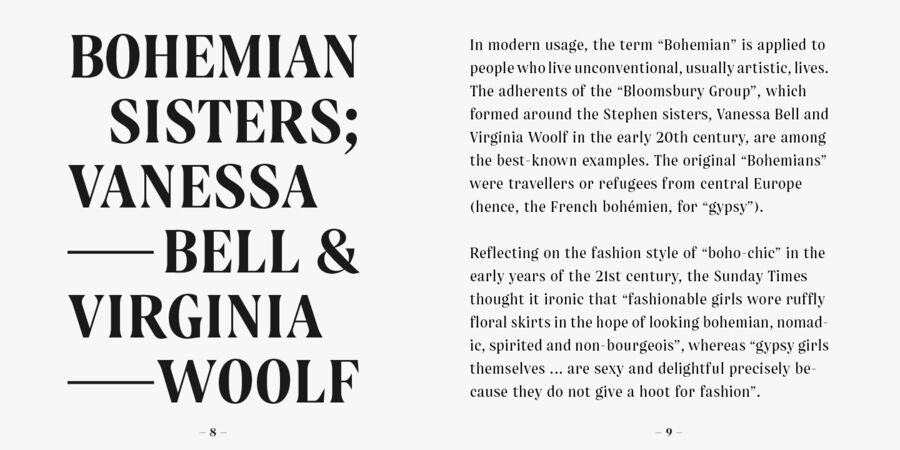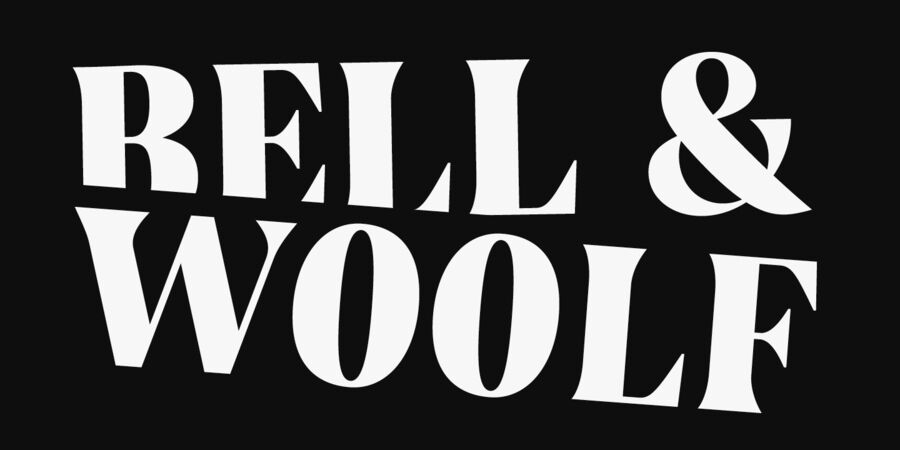
Boita – це елегантна акцидентна антиква. Гарнітура створена для сильного впливу, вона відрізняється великою висотою рядкових літер, високою контрастністю, впевненими формами й гострими зарубками. Його стислі пропорції дозволяють привертати увагу навіть в умовах обмеженого простору. Boita формує на сторінці «гладку, як оксамит» текстуру, зберігаючи відчуття виразної впевненості. Сімейство підтримує як латинку, так і кирилицю. Шрифт розробила Марія Пігулевська у 2016 році. Botia™ є торговою маркою компанії The Northern Block.
Асоціації з сімейством шрифтів BoitaОсобистість і характер гарнітури:
серйозний, статичний, традиційний, класичний, аристократичний, салонний, урочистий, дзвінкий, благородний, якісний, культурний, гострий, ностальгічний, старомодний, багатий, консервативний, світський, сріблястий, майстерний, розкішний, дорогий, ефектний, срібний, крихкий, прозорий, тонкий, елітний, модний, худий, джентльменський, пафосний, добірний, гладенький, гнучкий, естетичний, витончений, художній, знаменитий, дорогоцінний, оригінальний, красивий, комільфо, сексуальний, старовинний, історичний, солідний, стійкий, гордий, виразний, переконливий, важливий, щільний, впевнений, міцний, амбітний, кінематографічний, екстравагантний, яскравий, помітний, твердий, авторитетний, сильний, гучний, тісний
готель, вино, ресторан, комільфо, музей, розкіш, срібло, мода, люкс, література, годинник, бутік, преміум, культура, мистецтво, художник, музика, скульптура, опера, поезія, косметика, краса, алкоголь, коньяк, шоколад, прикраса, ювелір, коштовності, сервіровка, фарба, чай, кава, живопис, Біблія, детектив, Трофей, нагорода, захід сонця, костюм, краватка, обід, вечеря, кіно, гроші, банк, банкнота, монета, концерт, віскі, вечір, влада, ром Гарнітура має ознаки стилів: